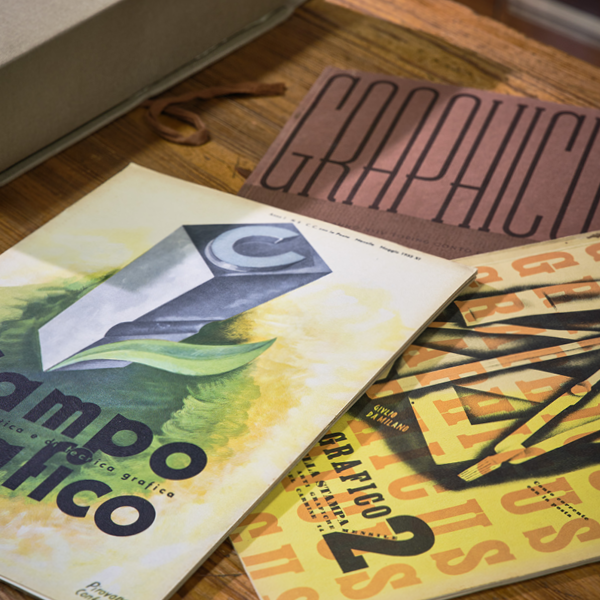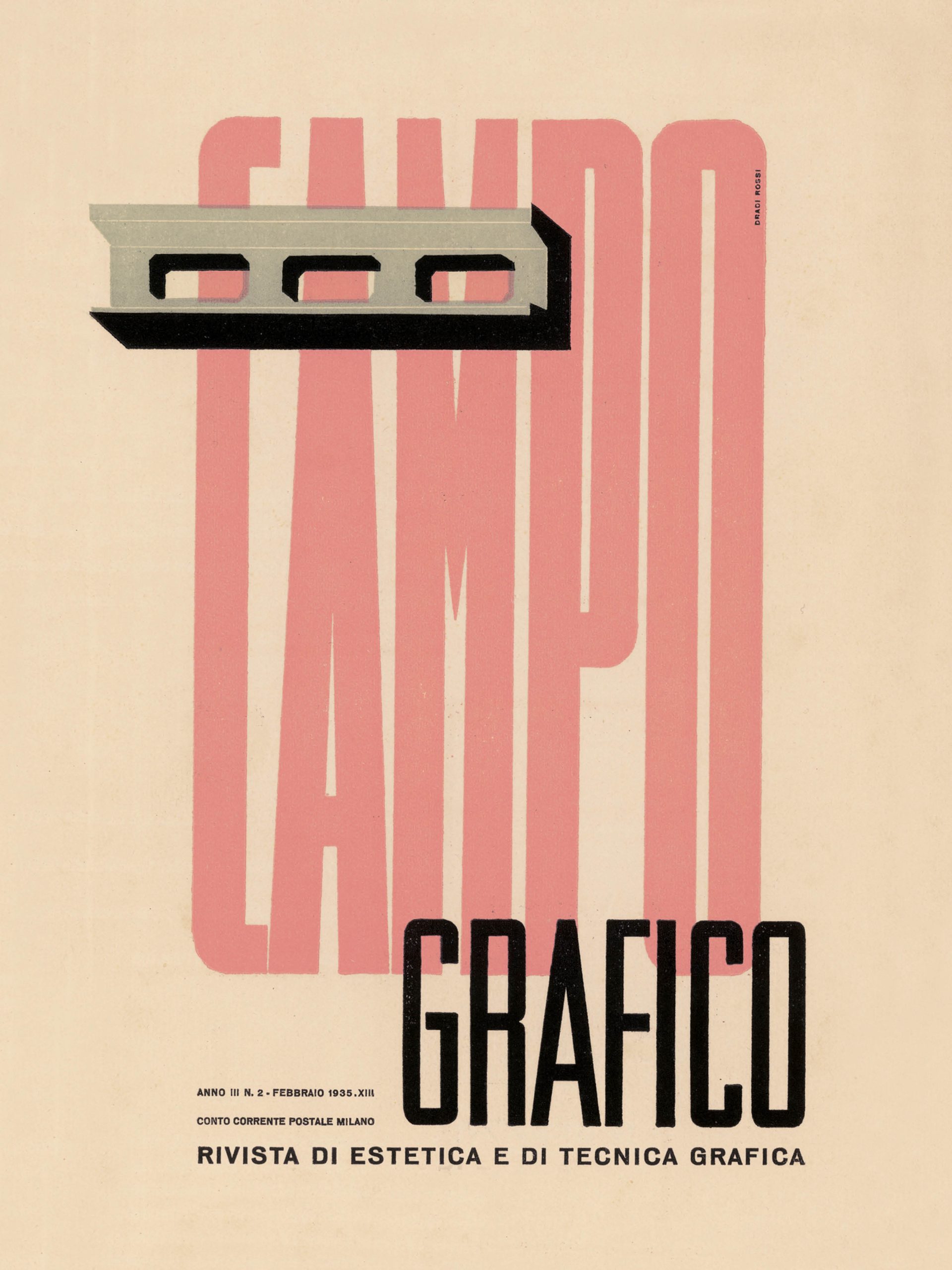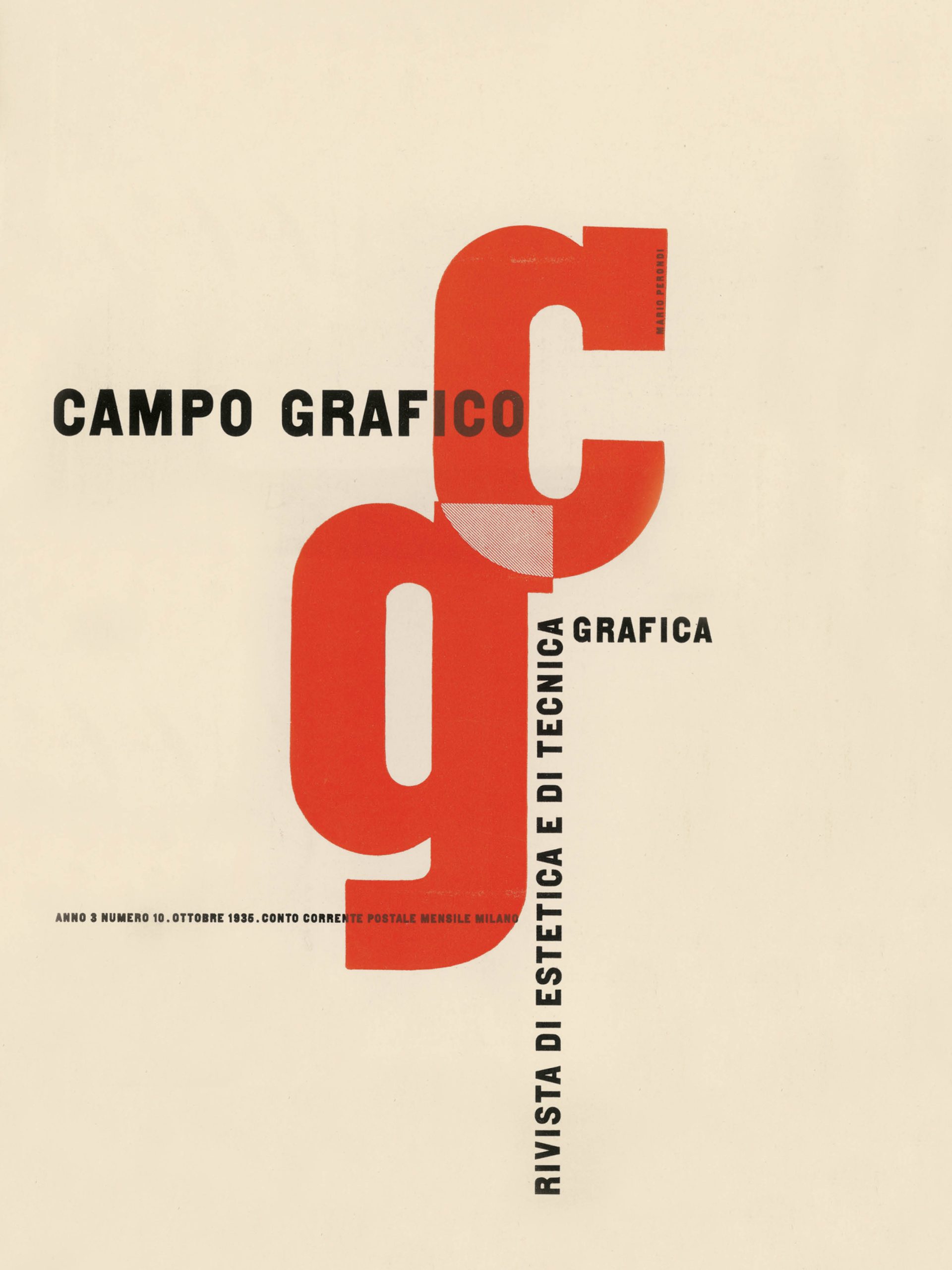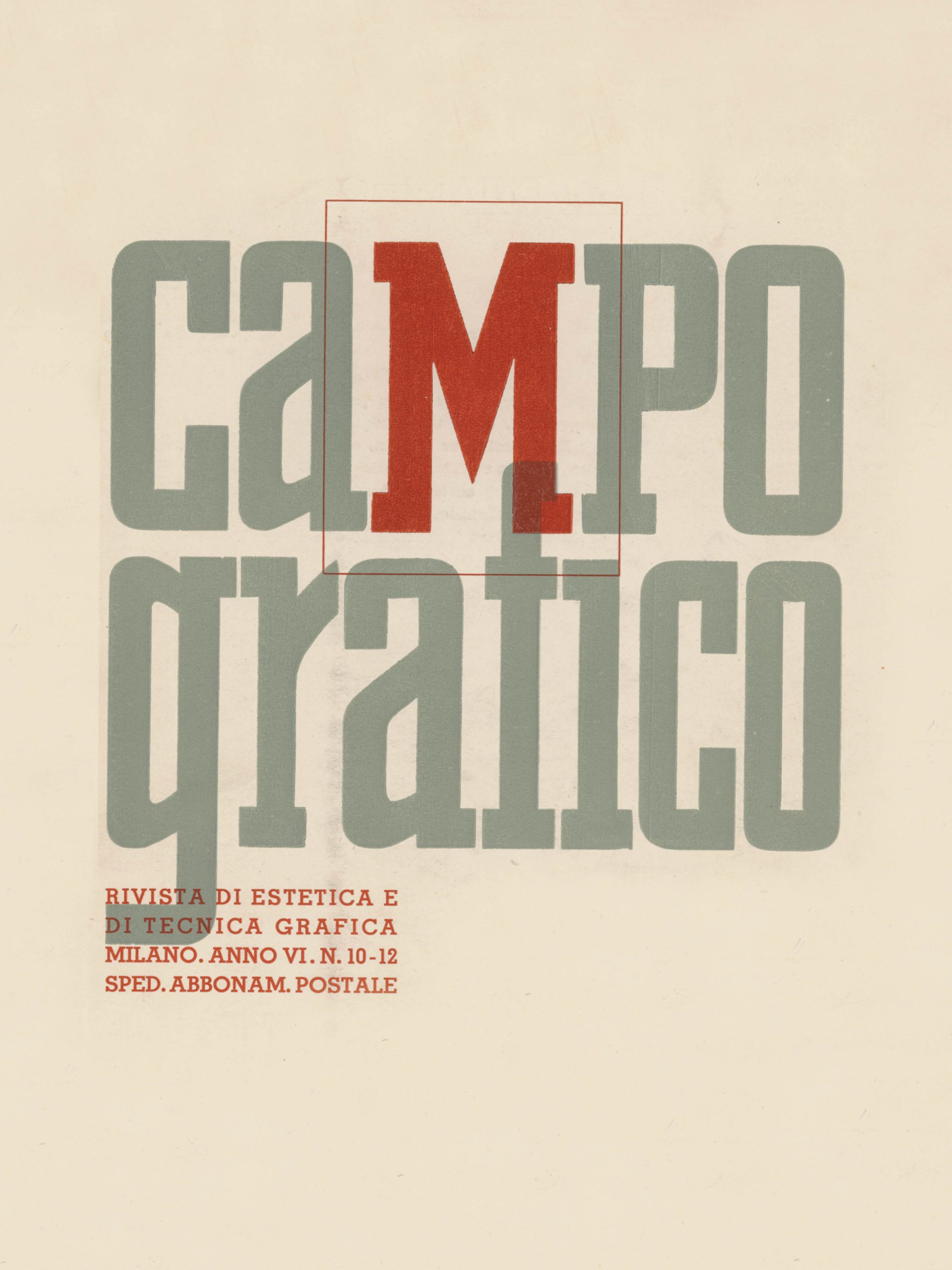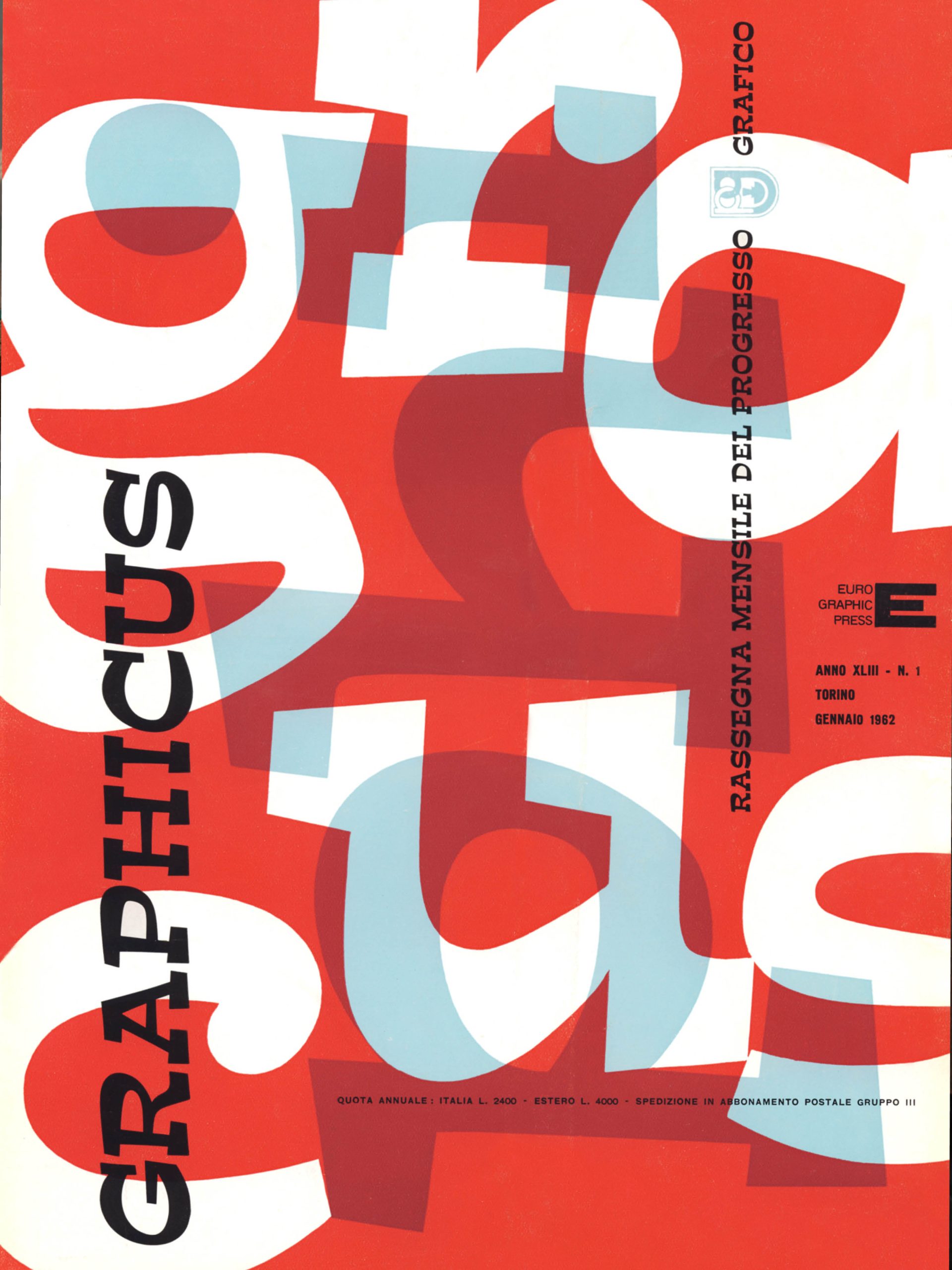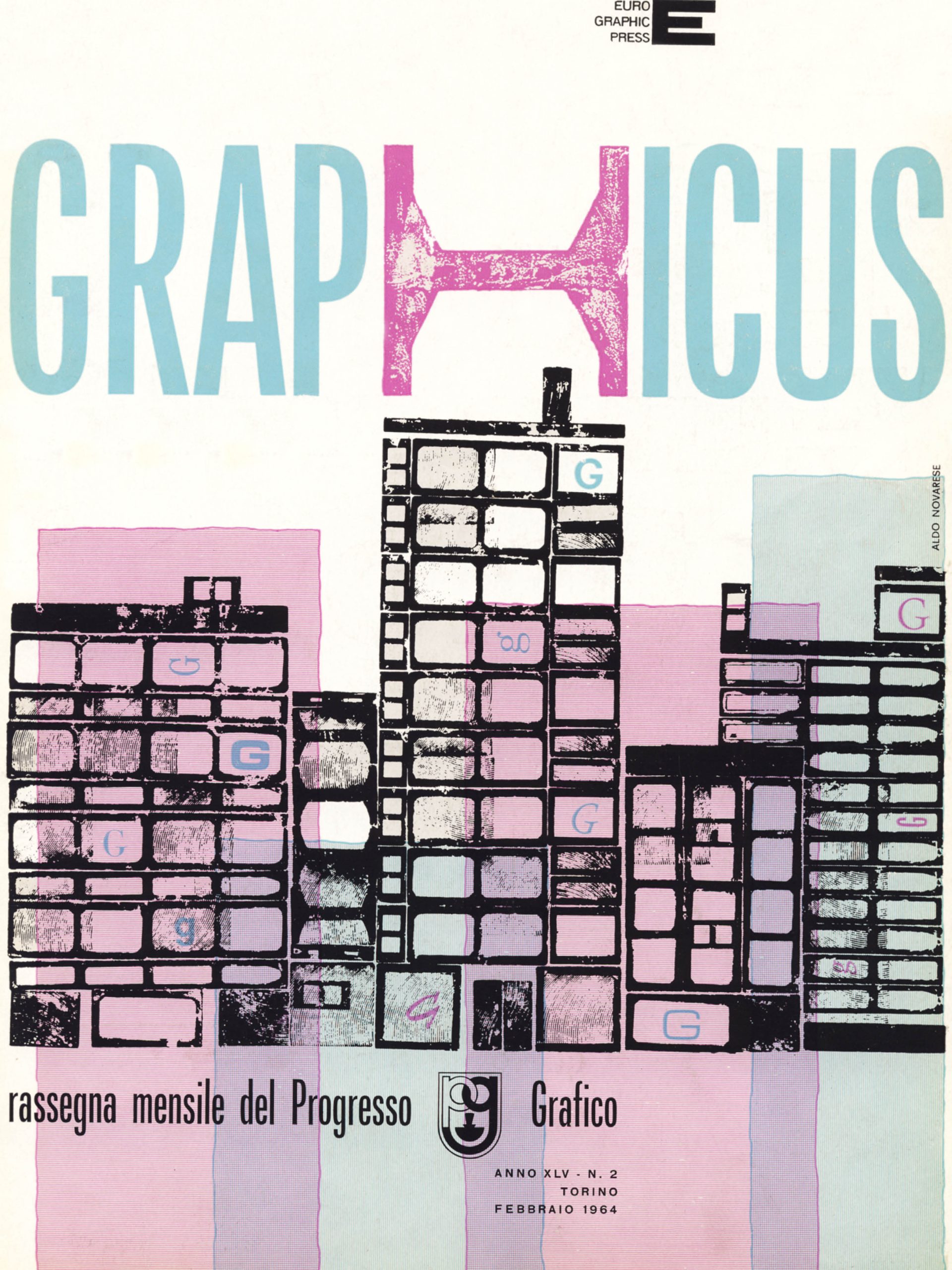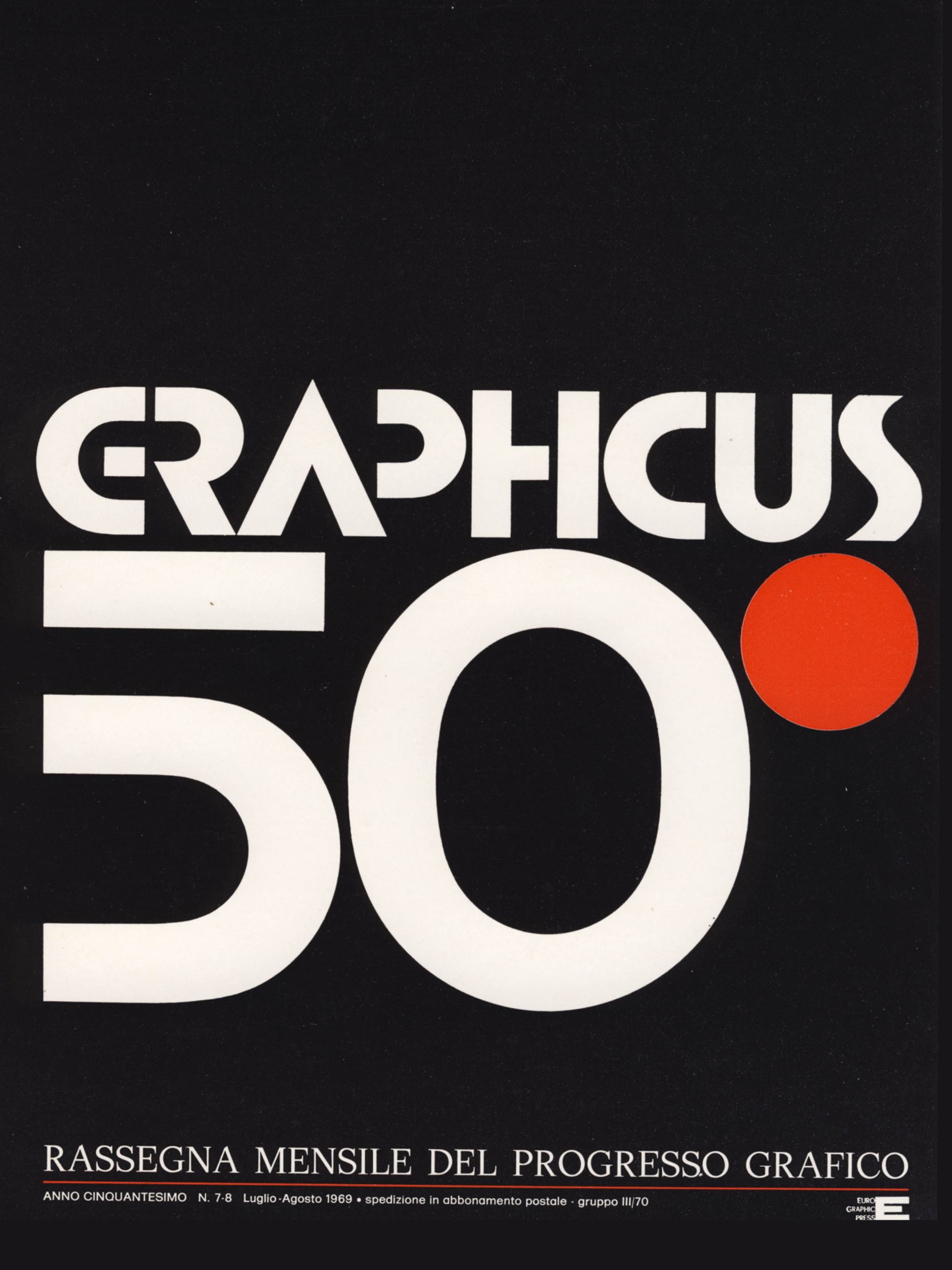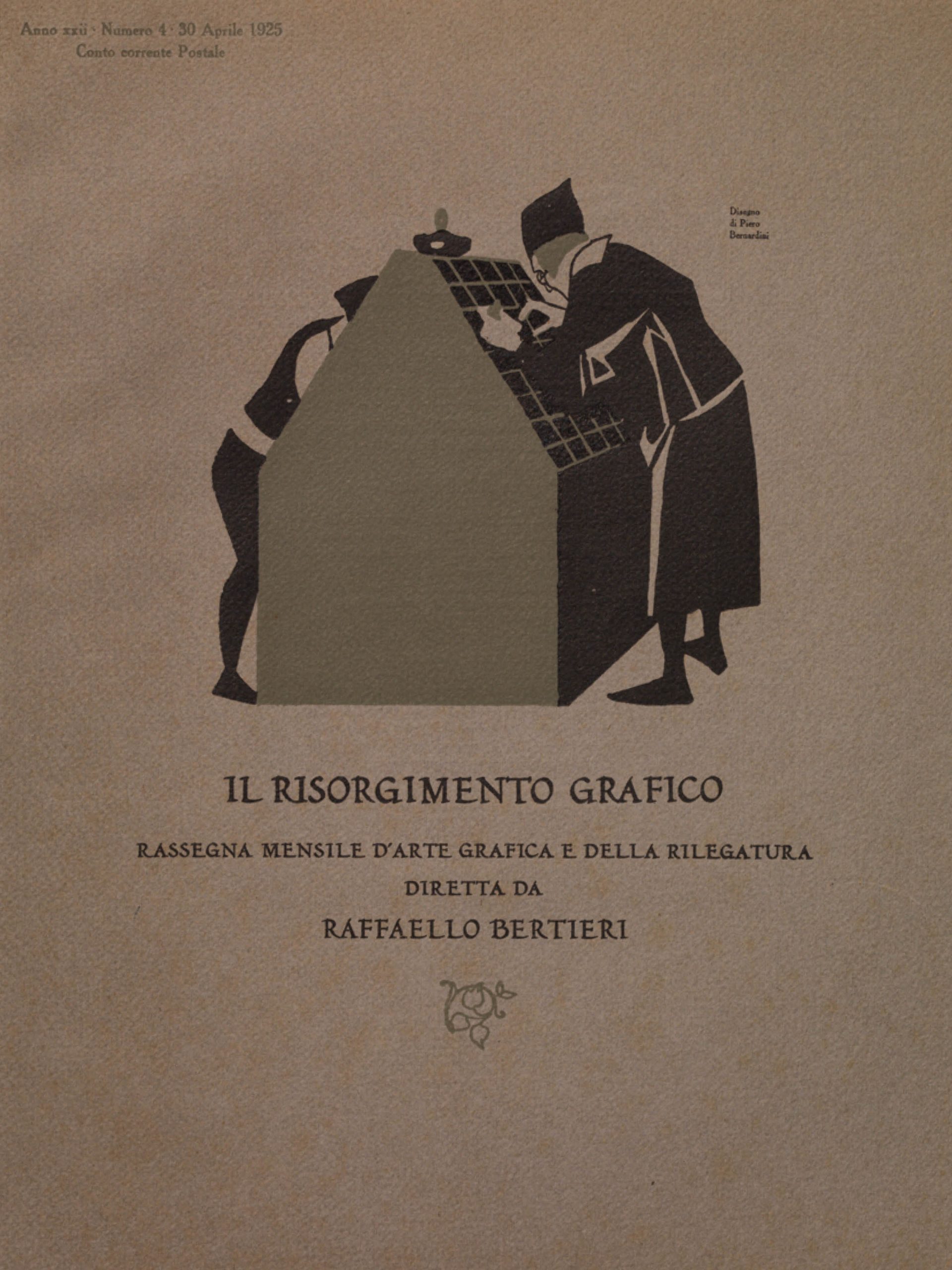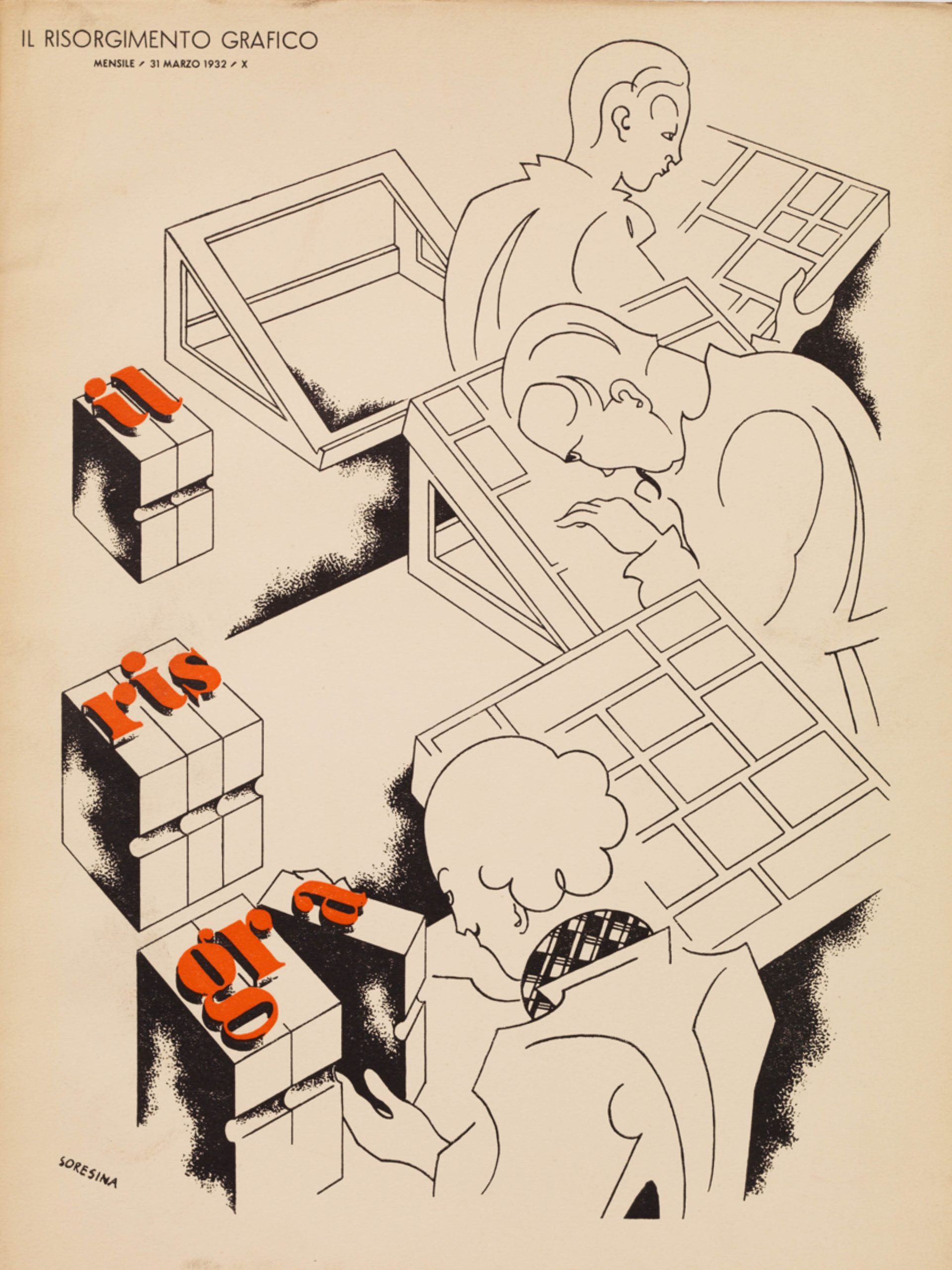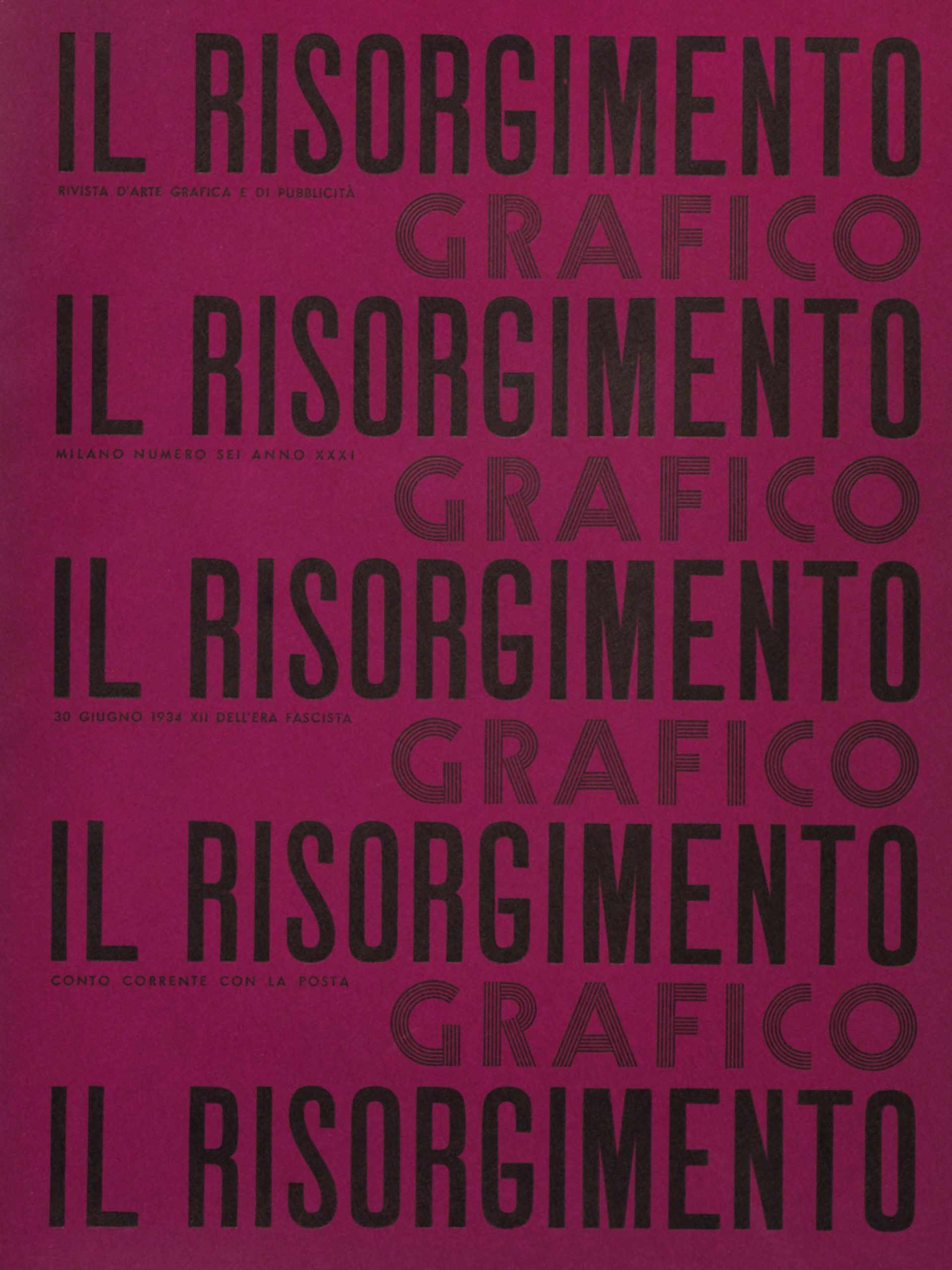
Insieme ai campionari, le riviste sono le tipologie di stampato più studiate da chi desidera approfondire i processi di evoluzione dei caratteri e le modalità di comunicazione utilizzate da tipografie e fonderie. Ricordiamo soprattutto quattro riviste: Campo Grafico, Graphicus, Il Risorgimento Grafico, Archivio Tipografico. Attive in momenti diversi a partire dalla fine del 1800, queste riviste avevano come obiettivo la raccolta di testi, articoli e immagini che raccontassero quanto accadeva in Italia nel mondo della tipografia. Il Risorgimento Grafico, diretta a lungo da Raffaello Bertieri, era la più orientata alla tradizione. Campo Grafico manteneva una visione di più ampio respiro e abbracciava le avanguardie europee, combinando stampa tipografica, stampa offset, serigrafia e fotografia. In particolare, Campo Grafico è riconosciuta come la rivista più ambiziosa perché progettata e stampata direttamente dai tipografi. Archivio Tipografico e Graphicus erano legate alla Fonderia Nebiolo e al mondo accademico torinese; molte copertine di Graphicus tra gli anni ’50 e ’60 sono state disegnate da Aldo Novarese.